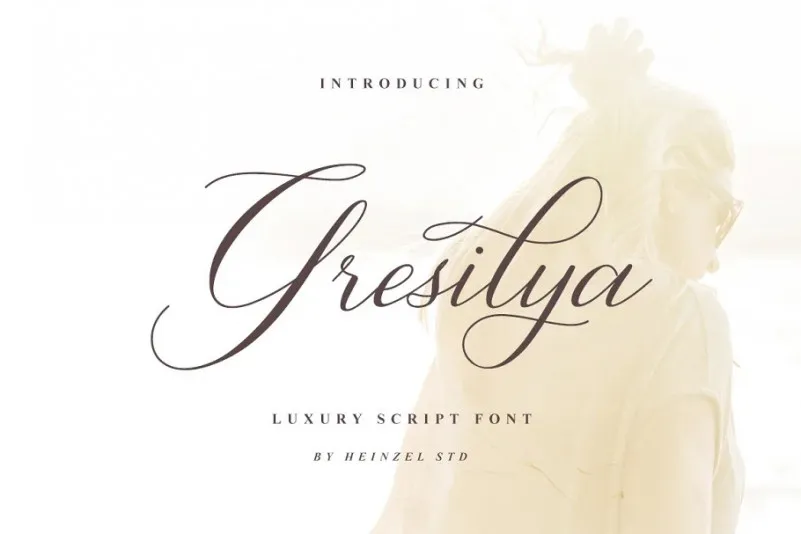
A Gresilya Font é uma opção atraente para aqueles que buscam algo moderno e elegante na categoria de fóruns script. Desenvolvida pelo 99designs, esta fonte traz um toque sofisticado à qualquer projeto. Com detalhes cuidadosamente projetados, ela oferece uma variedade de alternativas em linha com a tipografia clássica da caligrafia, dando ao seu design um sentimento contemporâneo e fresco sem perder o charme da tradicional escrita. Ideal para designers buscando um estilo elegante que também reflete a modernidade, a Gresilya Font é uma escolha inteligente. Com sua variedade de linhas suaves e belos caracteres, ela permite que você personalize cada projeto de acordo com suas necessidades. Além disso, o fato de ser PUA (Unicode) codificado significa que você pode acessar facilmente todos os glyphes desta fonte. Essa característica torna a Gresilya Font uma excelente opção para aqueles que buscam qualidade e sofisticação em cada letra escrita com ela.